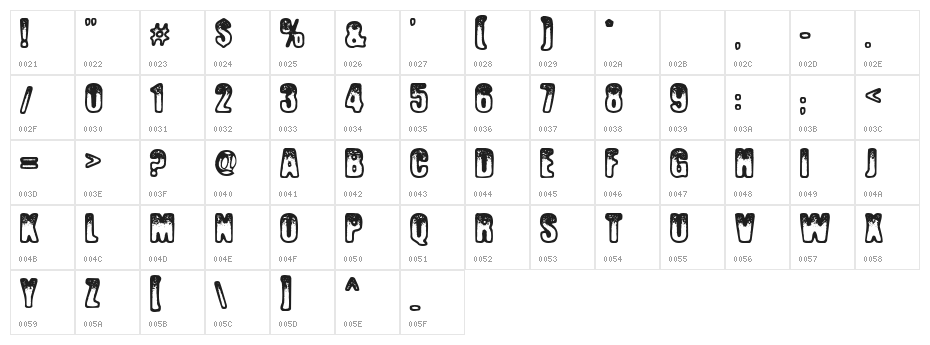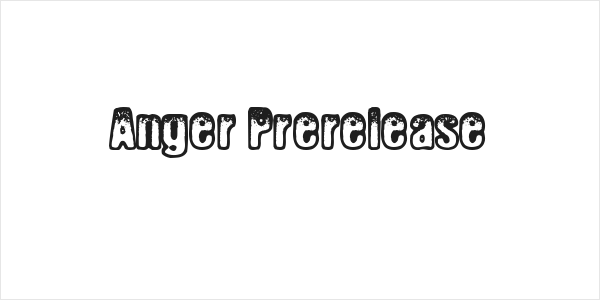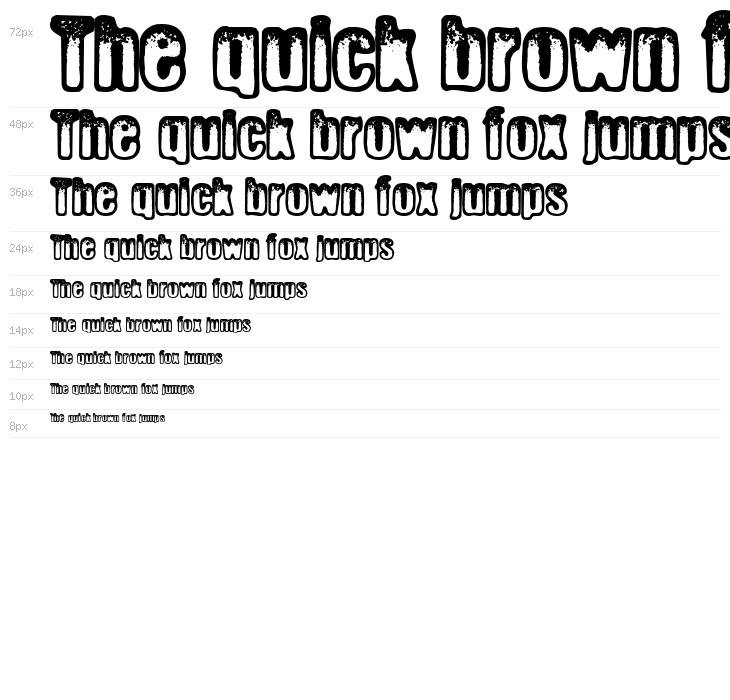
Anger Prerelease Font
| Categorie | Distorted Eroded |
| Stile generale | Grunge, Edgy |
| Progetti proposti | Ideal for projects requiring a strong, edgy look such as music album covers, posters, or branding for extreme sports. |